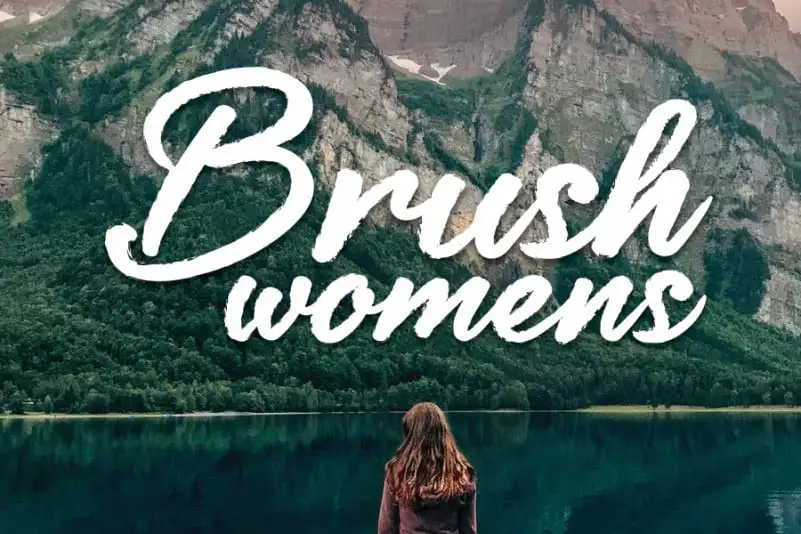
Brush womens Script Font – Download Grátis
A Brush Women’s Script Font é uma elegante escolha para os projetos digitais e manuais. Criada utilizando um pincel, essa fonte brush oferece um ar casual e divertido que torna-a ideal para todos os seus logotipos, identidades de marca e projetos em redes sociais. O design limpo e a pitada de criatividade da Brush Women’s Script Font garantem uma presença forte e única nas mídias digitais ou em projetos manuais como decoração e DIY. Perfeito para estilos jovens e atuais, essa fonte traz aos seus projetos um toque especial que vai desde a identificação de marcas até os tópicos mais criativos em sua página de redes sociais. Além disso, ela é uma ótima opção para qualquer projeto DIY ou crafts, onde deseja dar um toque diferenciado e divertido aos projetos. Seja você designer gráfico ou amante de DIY, a Brush Women’s Script Font oferece a liberdade de expressar seu estilo pessoal. Sua versatilidade faz dela uma escolha muito desejada para qualquer projeto que busque um ar criativo e descontraído.